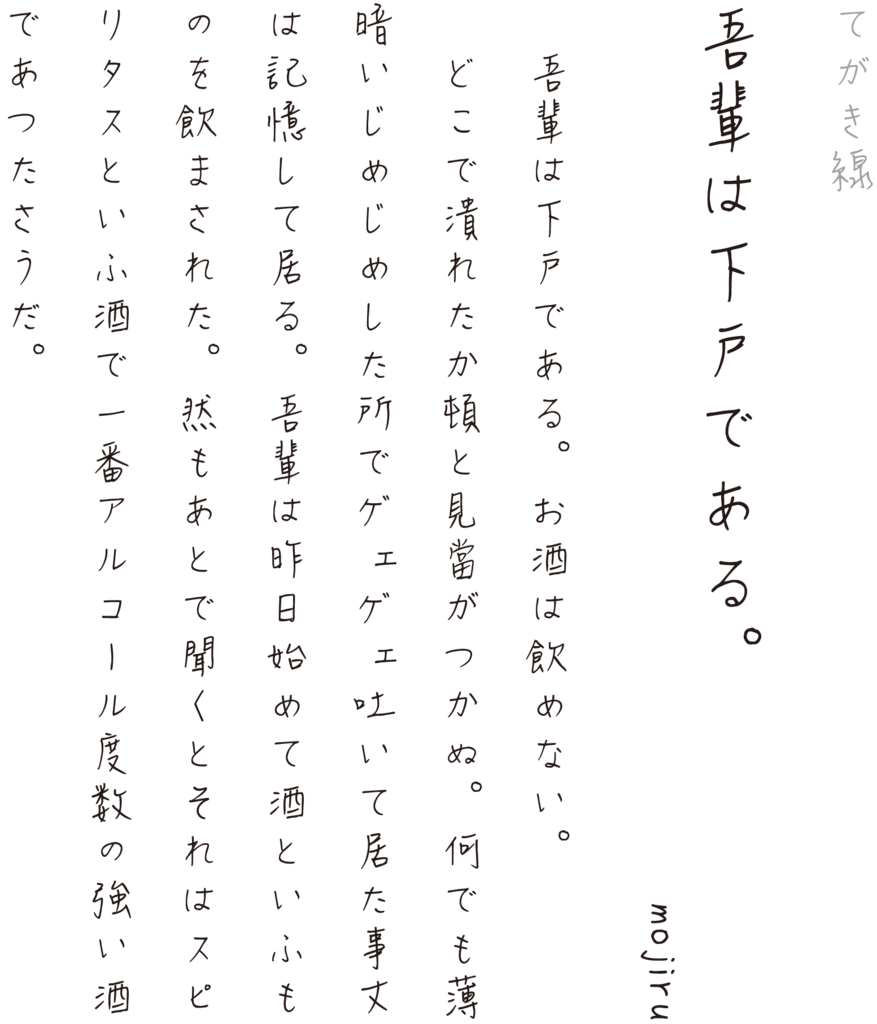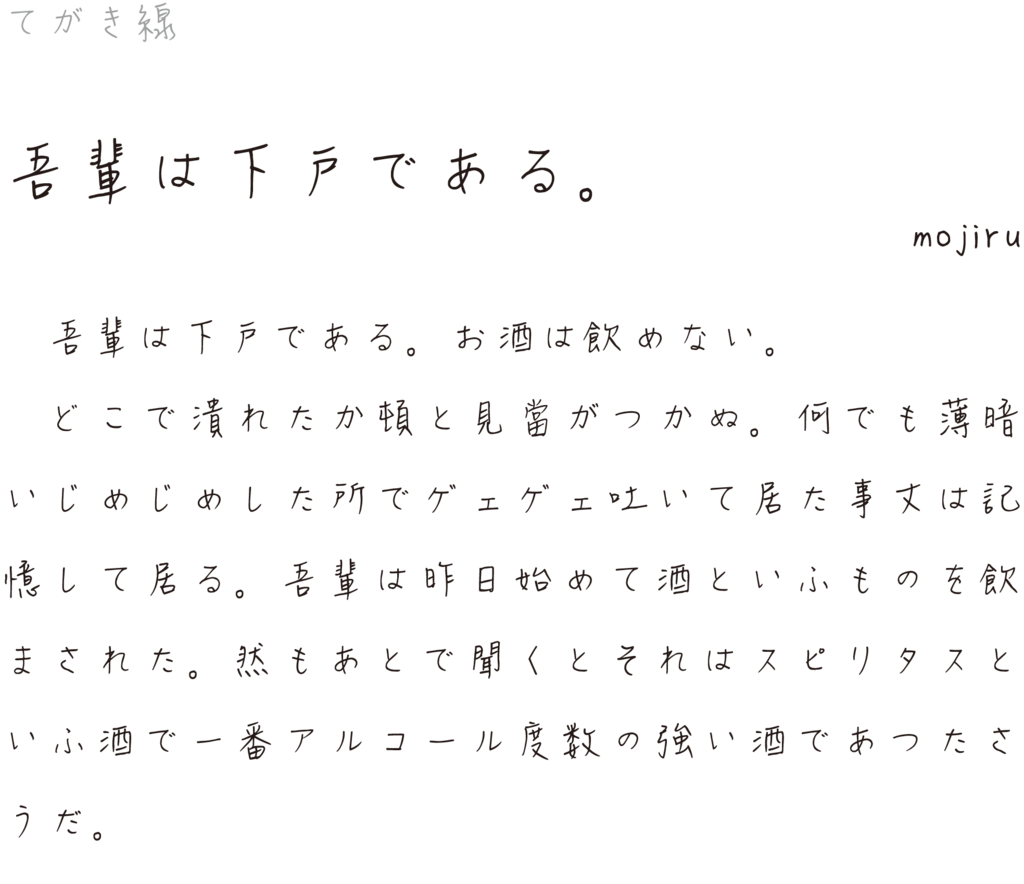
てがき線
「てがき線」は、縦長の字形で一点一画をはっきりさせながらも手書きの自然さを持たせた書体。やや右上がりに書くようなクセを取り入れることで、全体にスマートな印象を持たせている。詩集や年賀状などの印刷物にスマートな印象を与えたい場合にオススメ。後に「てがき線」をベースにした書体「ハンジペン」がリリースされた。